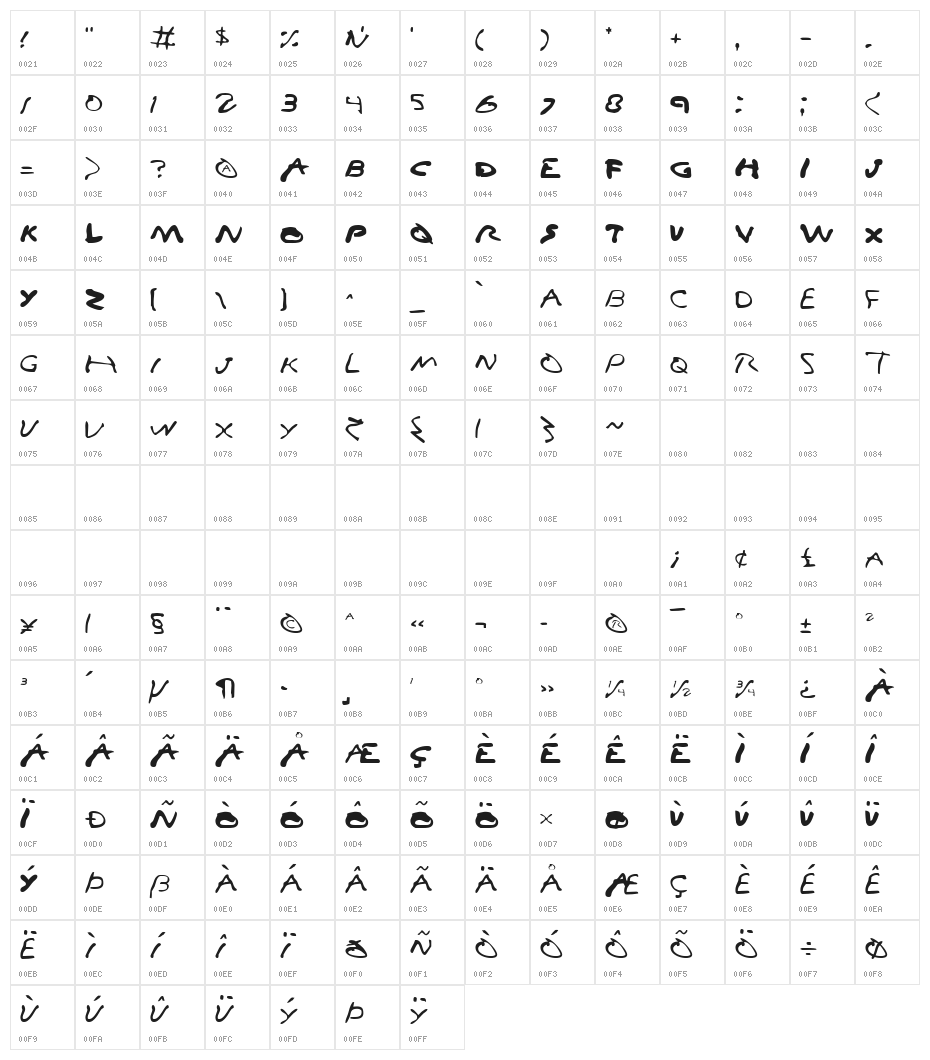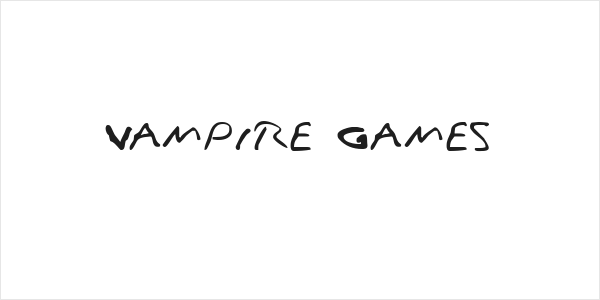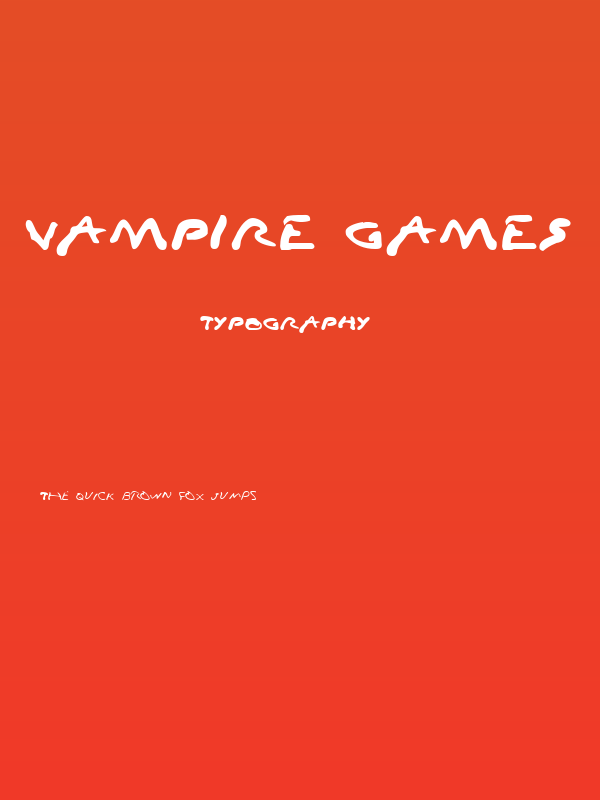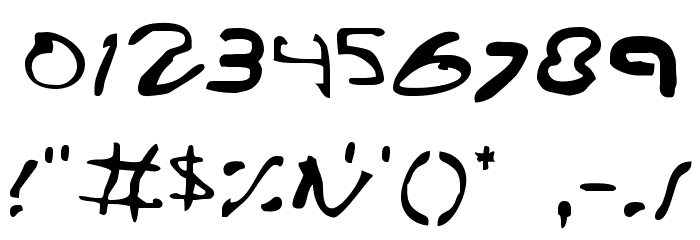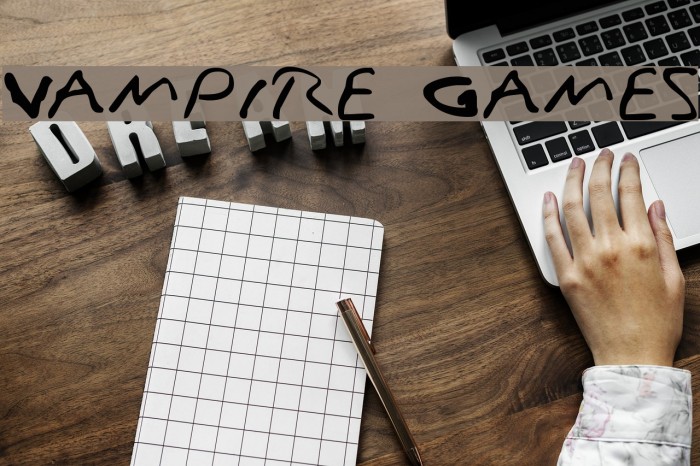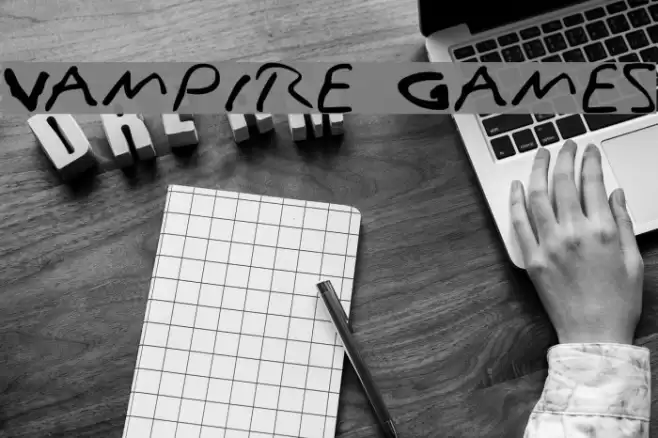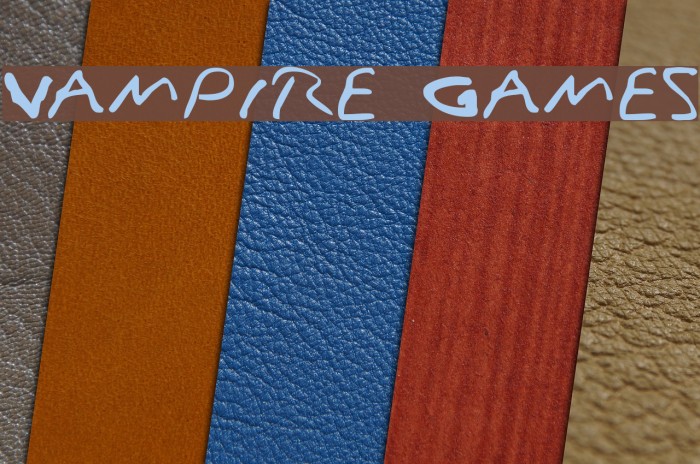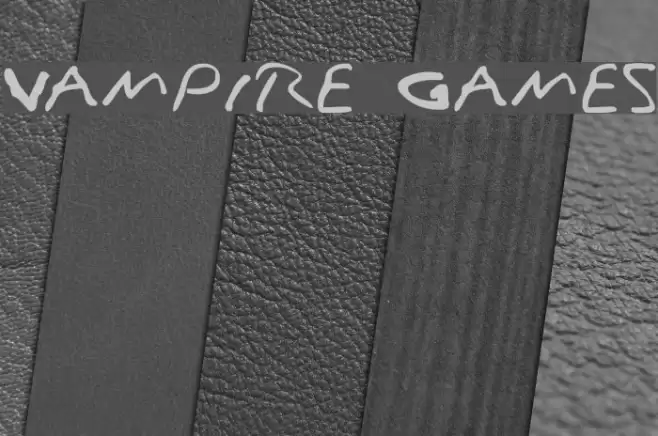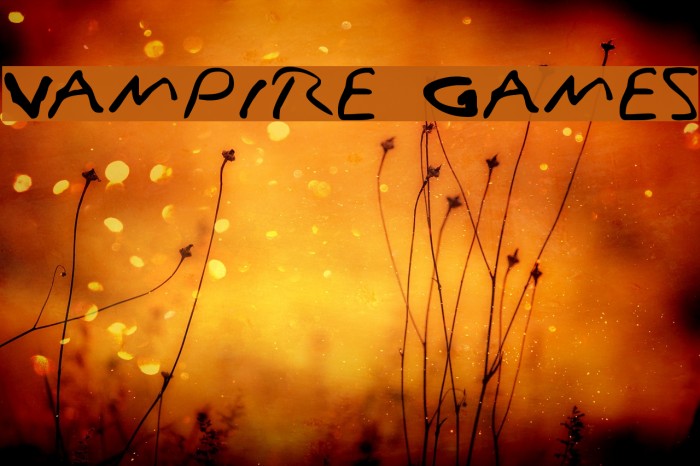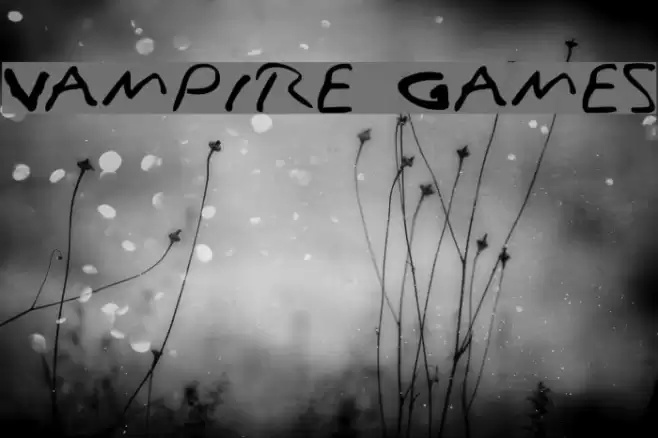
Vampire Games Font
✎ Quirky
| Progetti proposti | Ideal for game titles, posters, creative designs, and any project needing a bold, attention-grabbing font. |